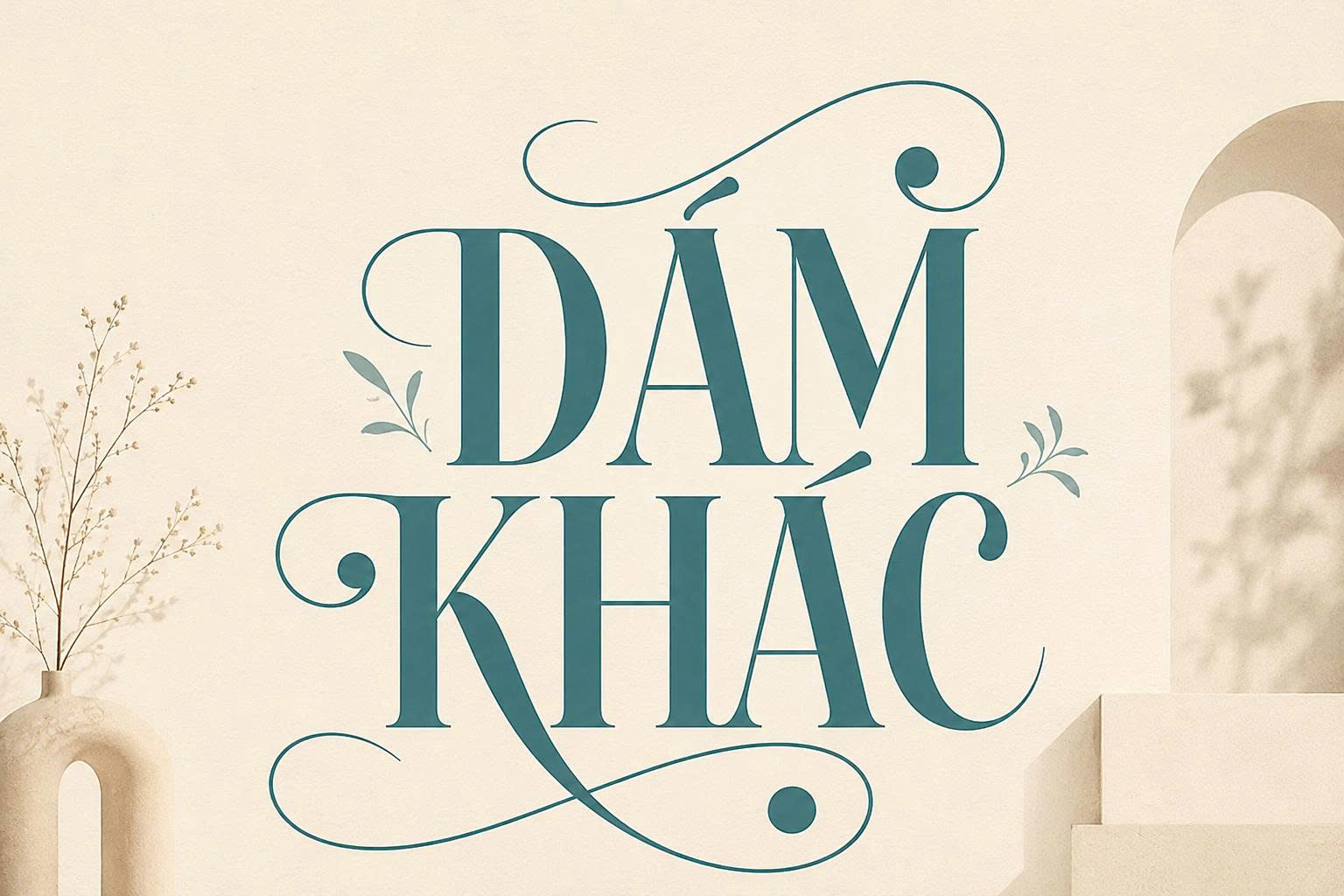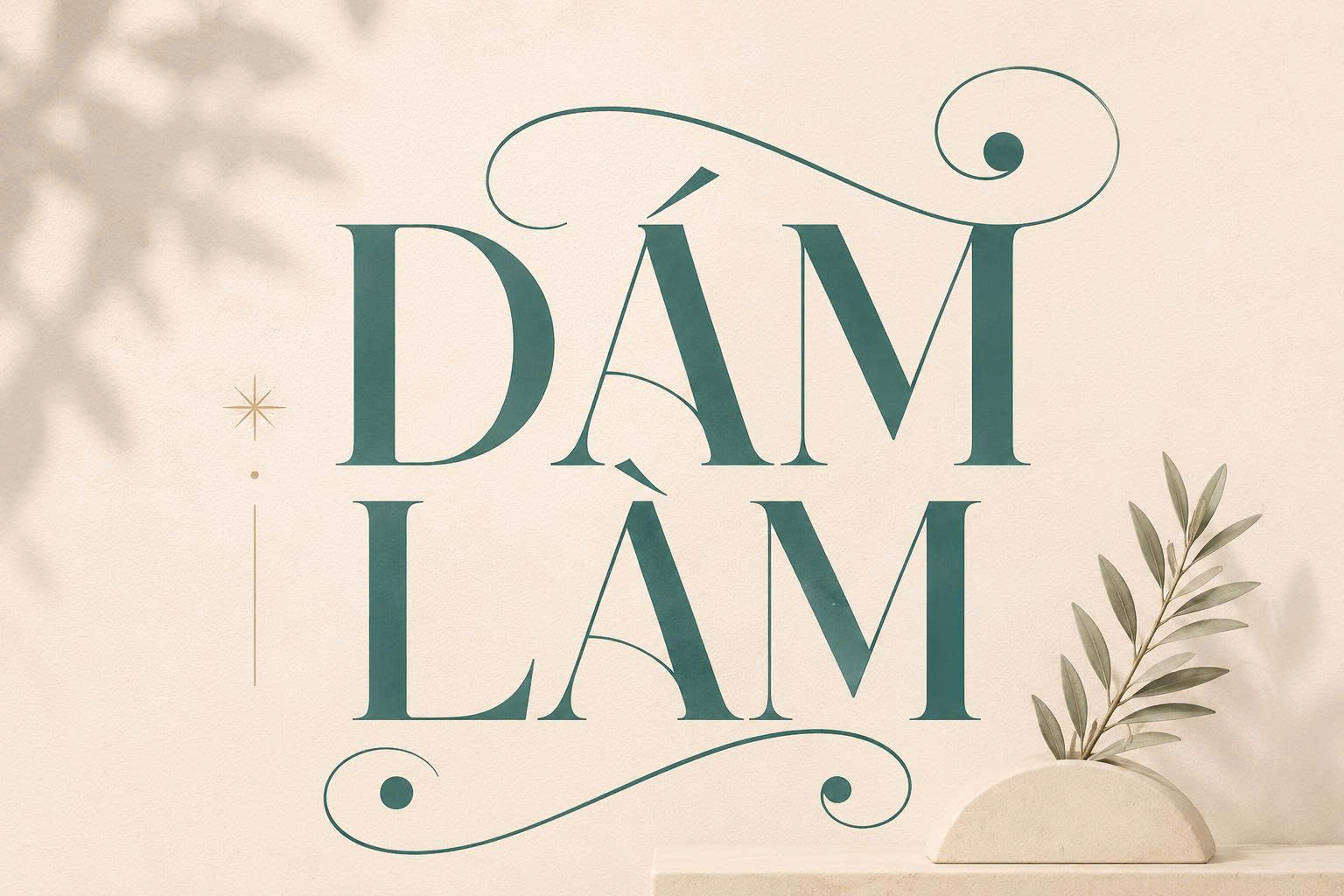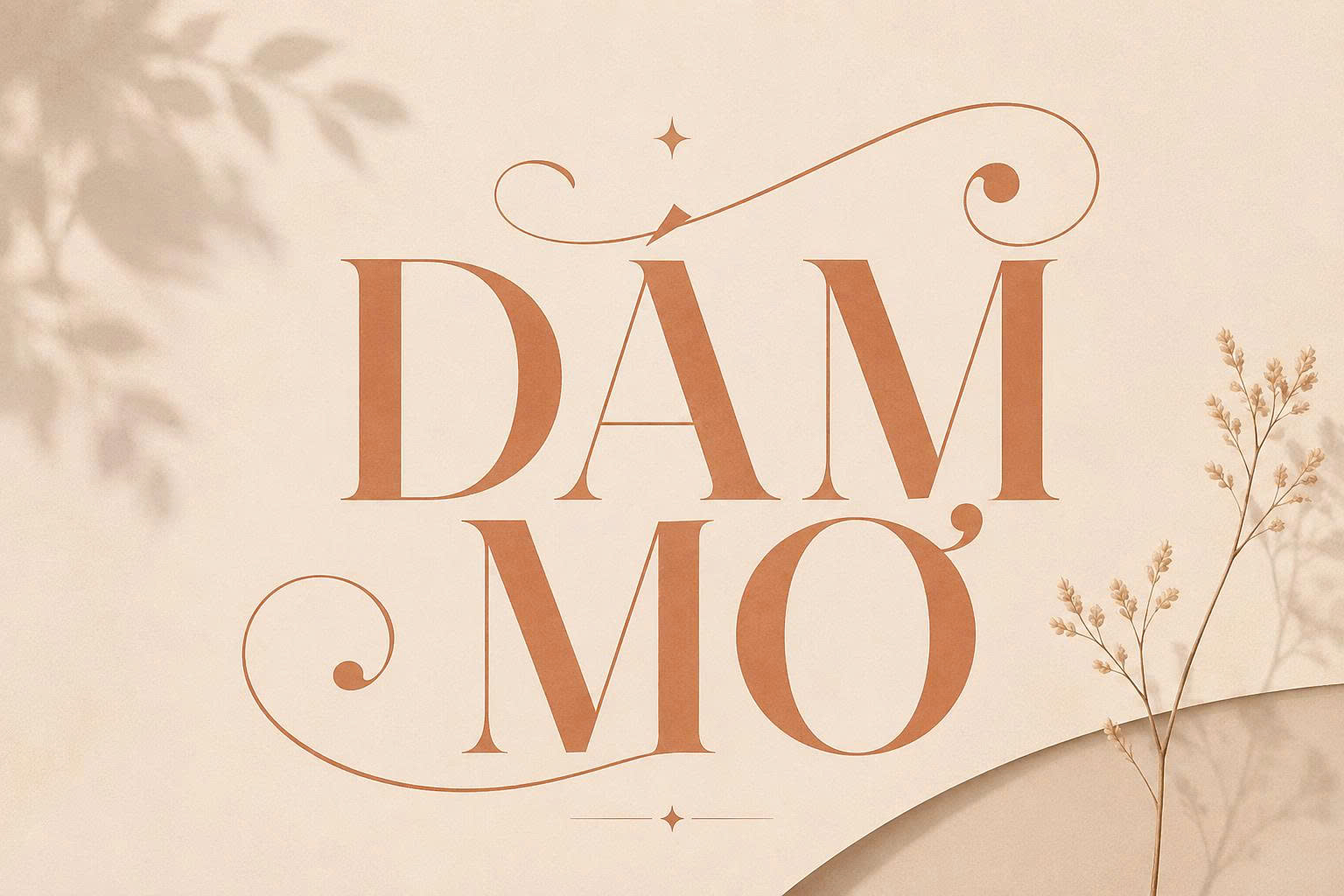
Font Việt hóa SVN Morva là bộ phông chữ có chân (Serif) hiện đại mang phong cách nghệ thuật độc đáo, nổi bật với những đường nét thanh mảnh, uốn lượn và độ tương phản nét thanh đậm cực kỳ tinh tế. Được lấy cảm hứng từ phong cách thời trang cao cấp và đồ họa tạp chí, SVN Morva là lựa chọn hoàn mỹ cho các dự án thiết kế logo, bao bì mỹ phẩm và nhận diện thương hiệu cần sự sang trọng, nữ tính. Doozypack.vn chia sẻ link tải font SVN Morva chuẩn, hỗ trợ đầy đủ tiếng Việt để bạn nâng tầm đẳng cấp cho mọi bản thiết kế in ấn.
Đặc điểm thẩm mỹ nghệ thuật của font SVN Morva Việt hóa
SVN Morva không chỉ là một phông chữ Serif thông thường; nó là sự kết hợp giữa nét cổ điển quý tộc và tinh thần sáng tạo đương đại, mang lại diện mạo vô cùng lôi cuốn.
Đường nét uốn lượn và cấu trúc chữ phá cách
Đặc trưng lớn nhất của font SVN Morva Việt hóa là các chi tiết biến tấu ở những ký tự như ‘a’, ‘g’, ‘f’ và ‘y’. Các đường cong được thiết kế mềm mại, tạo nên nhịp điệu Typography vô cùng bay bổng và có chiều sâu nghệ thuật. Cấu trúc chữ của Morva gợi nhắc đến các thương hiệu Luxury toàn cầu, mang lại cảm giác uy tín và gu thẩm mỹ thượng lưu ngay từ cái nhìn đầu tiên.
Mẫu chữ SVN Morva thanh lịch
Hệ thống dấu tiếng Việt được tinh chỉnh chỉn chu
Nằm trong bộ sưu tập SVN nổi tiếng, Morva đã được đội ngũ thiết kế tinh chỉnh lại hoàn toàn hệ thống dấu thanh tiếng Việt. Các dấu sắc, huyền, hỏi, ngã, nặng được thiết kế thanh mảnh, đặt ở vị trí cân đối hài hòa với thân chữ gốc, đảm bảo không làm mất đi độ thoáng và phong cách thanh lịch đặc trưng. Việc sử dụng bản Việt hóa chuẩn giúp bạn tự tin dàn trang cho các tiêu đề bao bì mà không lo lỗi font.
- Tạo dấu ấn thương hiệu độc bản: Phong cách Serif nghệ thuật của Morva giúp bao bì sản phẩm của bạn nổi bật hoàn toàn giữa hàng loạt đối thủ sử dụng phông chữ không chân thông thường.
- Nâng tầm giá trị sản phẩm: Morva mang lại diện mạo “Premium” ngay tức thì, đặc biệt hiệu quả khi ứng dụng cho ngành mỹ phẩm, nước hoa, nến thơm hoặc thời trang cao cấp.
- Tính linh hoạt trong dàn trang: Dù làm tiêu đề chính (Heading) hay các câu slogan ngắn, Morva vẫn giữ được độ sắc nét và tính thẩm mỹ tuyệt đối.